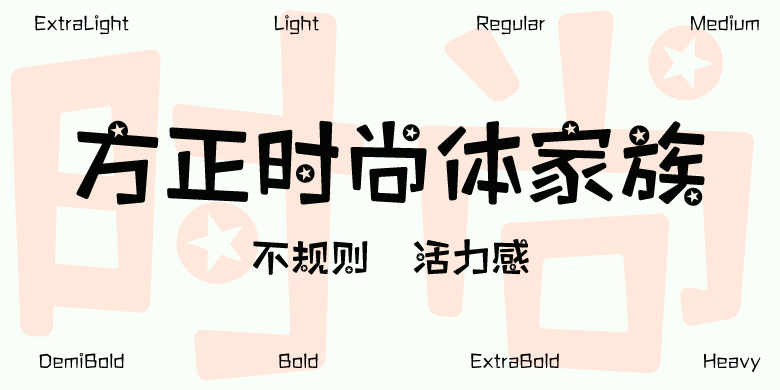
方正时尚体家族
时尚体的设计灵感源于一位斗牛勇士帽子上的小红星,勇敢斗牛勇士充满自信,骄傲的姿态,身手敏捷,充满能量和动感,这颗小红星不停上下左右,随着摆动,就像字体笔画不规则的跳高跳低。作者用圆体表达更充满人性化和活力感,加上小红星在每个字的不同位置出现,倍添年轻人的魅力,没法挡的感受。适合高档时尚饮料,牛奶产品,运动时装,运动鞋,时尚电脑产品,是一款活力的百搭字体。